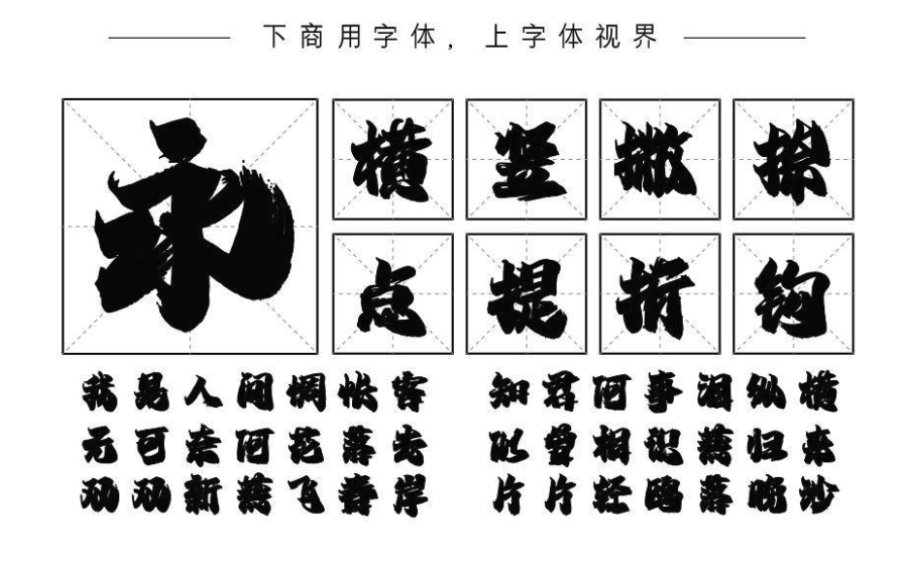
Aa醒狮体是一款以中国传统文化元素为基础设计的书法字体,其字形饱满、敦厚,充满力量感和气势。作为国潮字体的代表作之一,Aa醒狮体近年来备受瞩目。
这款字体的设计灵感源于中国传统的醒狮表演,字形中的每一个笔画都蕴含着强烈的动感和韵律感,完美地传达了中国文化的精髓和特点。同时,Aa醒狮体还融合了现代设计的元素,字体的整体风格显得时尚、简洁、大气,与现代社会的审美趋势不谋而合。
Aa醒狮体在品牌设计、文化宣传、广告设计等领域得到广泛应用,成为了国内外知名品牌的首选字体之一。此外,Aa醒狮体的应用范围也在不断扩展,如今已经涉及到书法作品、海报设计、数字媒体等多个领域。